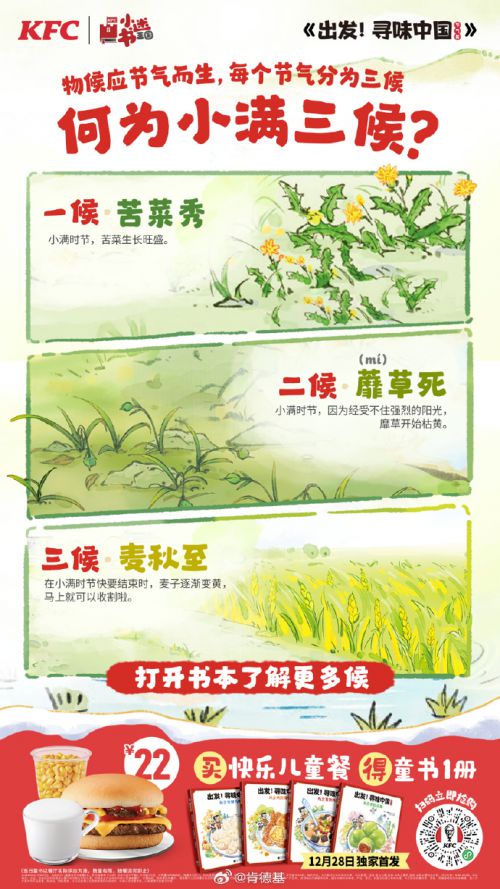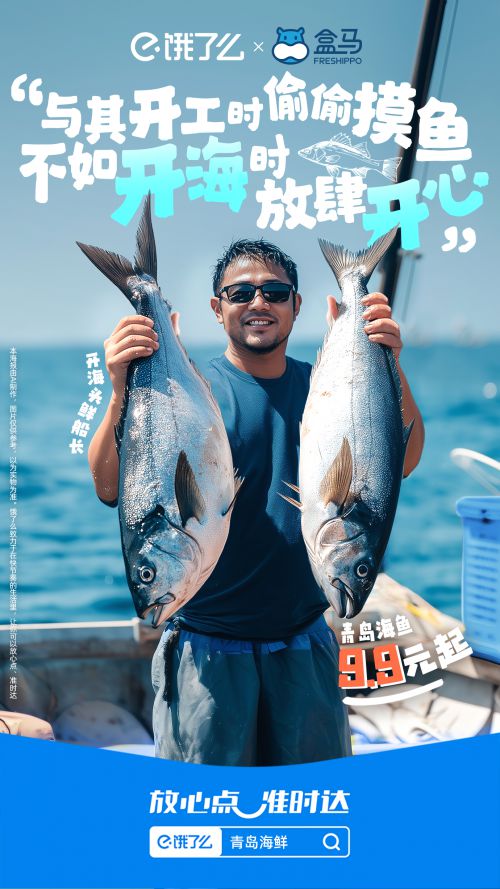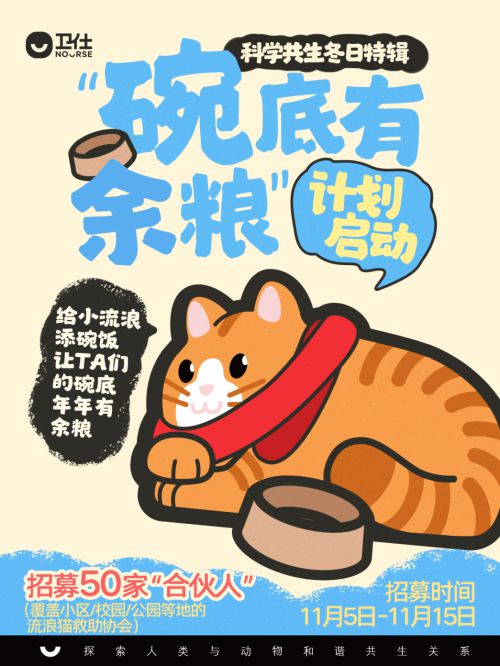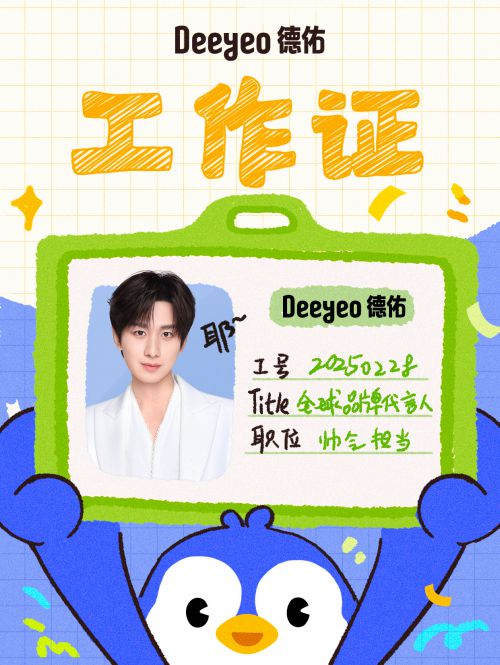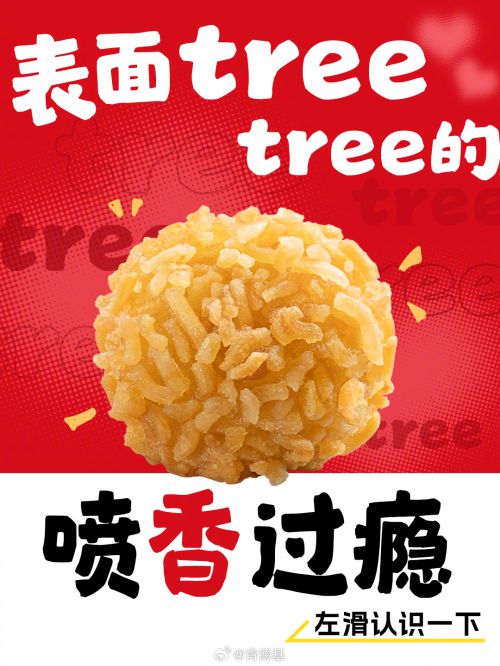
点字物语是一款融合中国风底蕴与可爱趣味的手写体字体,以书法笔触为基底,手写随性为韵脚,打造出兼具传统韵味与现代萌感的独特字形。字体结构方正稳健,重心居中且中宫适中,既保留手写体的自然灵动,又通过规整的字形框架形成踏实的块面感,笔势厚重饱满却不显臃肿,反而透着一股憨态可掬的亲和力。 点字物语在细节设计上暗藏巧思:笔画边缘的圆角处理柔化了线条棱角,起笔与收笔处的圆头形态更添稚气可爱,粗细均匀的笔触让整体视觉平衡协调,笔画间自然的连接过渡则赋予字体“看似统一,实则各有风情”的随性感——如同随手书写的便签,既有手写的温度,又不失设计的精致。无论是文创标题、海报设计还是社交媒体配图,点字物语都能以其“书法味+萌感”的双重气质,让文字瞬间充满生动张力,是追求个性与温度的会员商用设计优选字体。